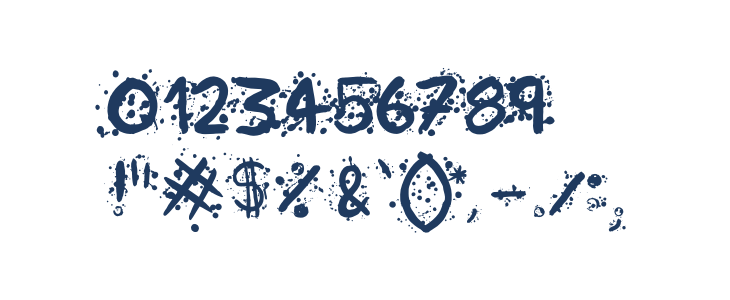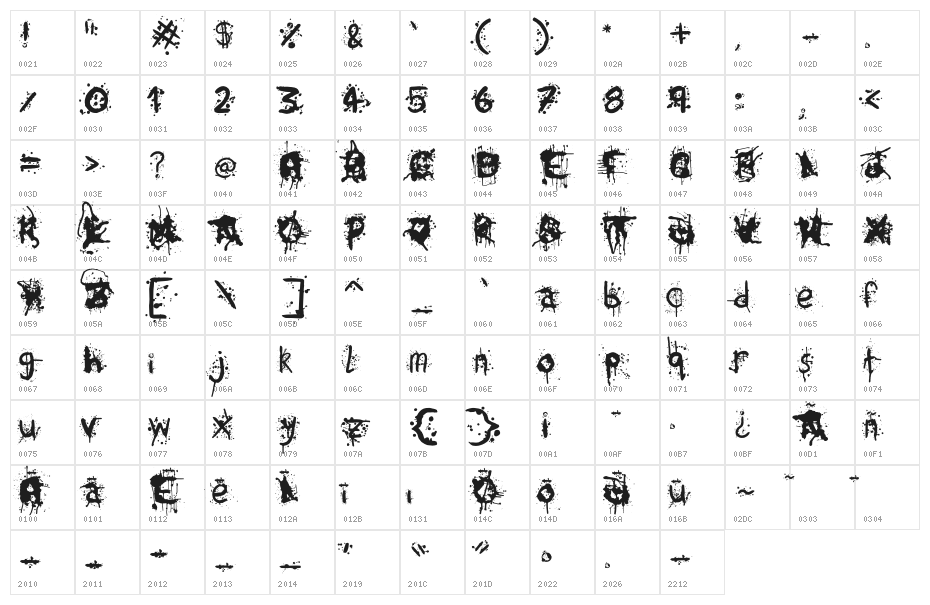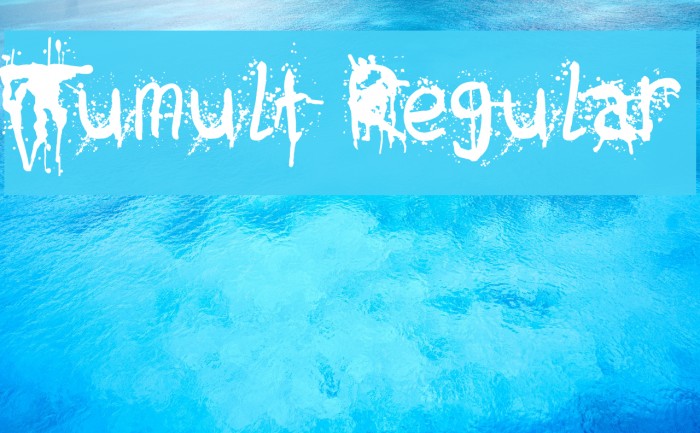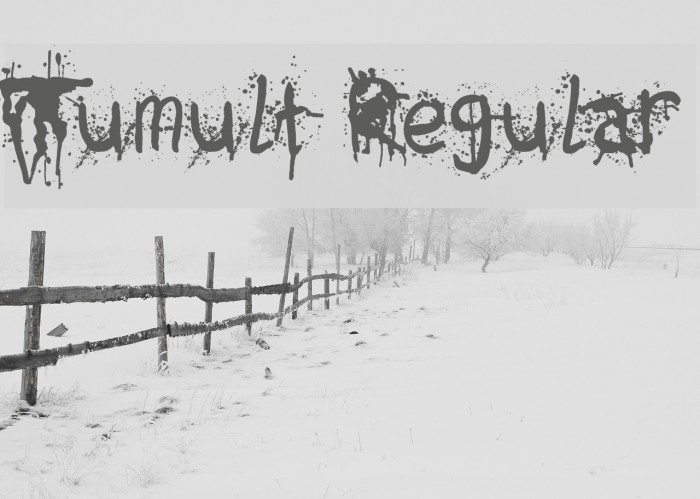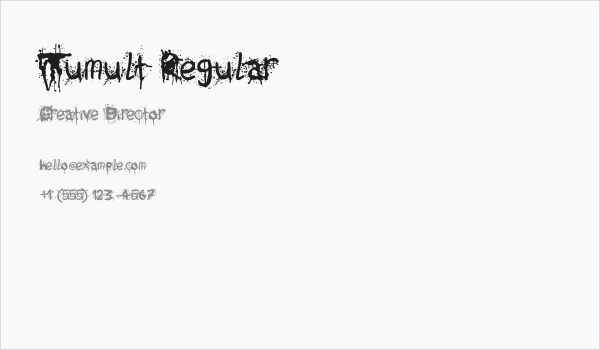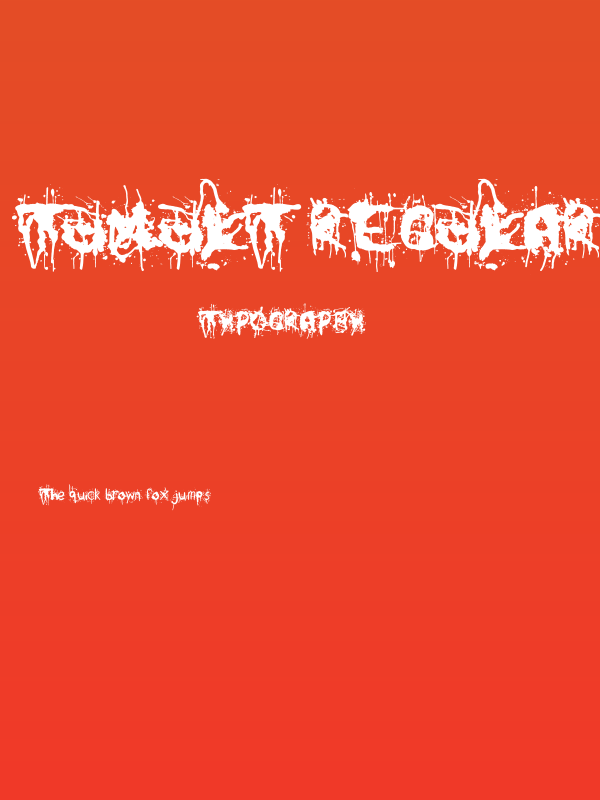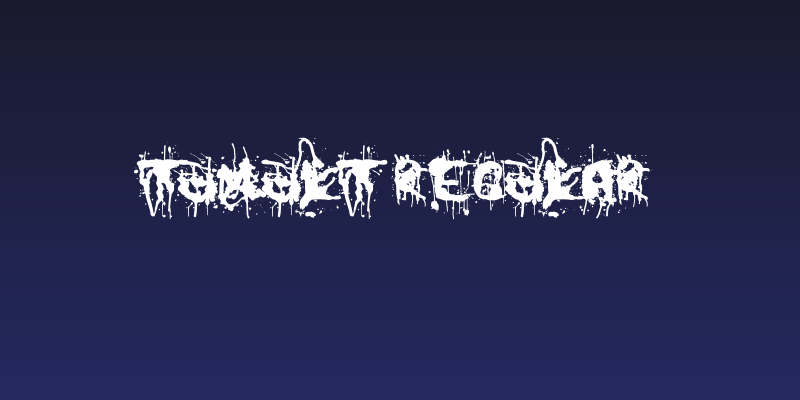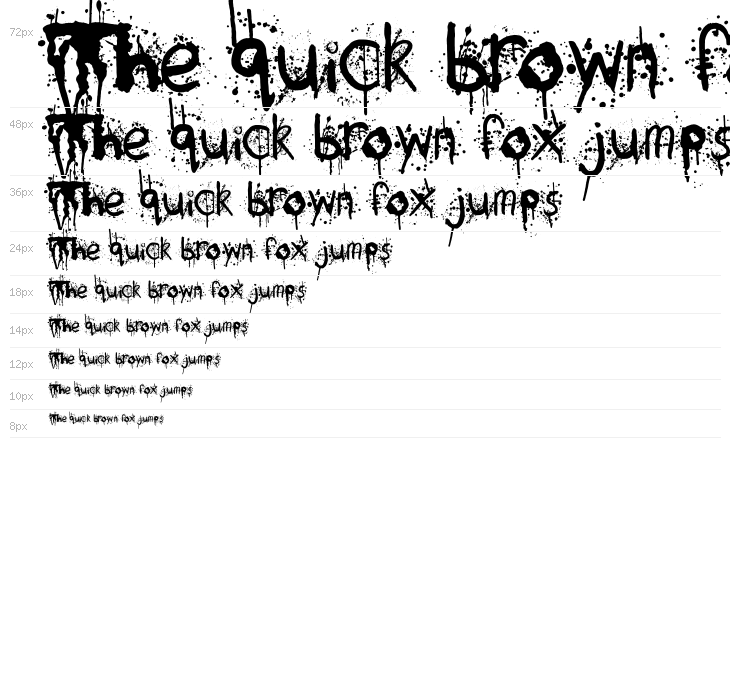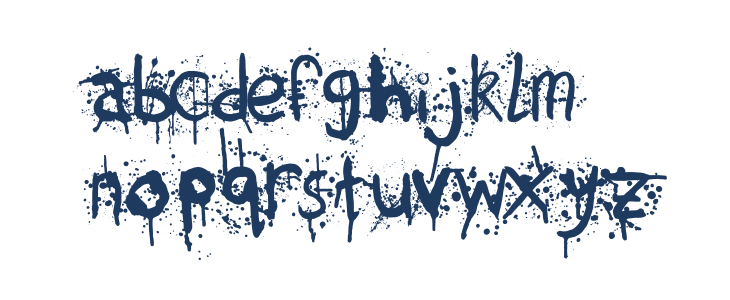
Tumult Regular Font
| Categorie | Graffiti |
| Stile generale | Urban, Grunge, Rebellious |
| Progetti proposti | Ideal for album covers, streetwear branding, urban-themed posters, and rebellious art projects. |